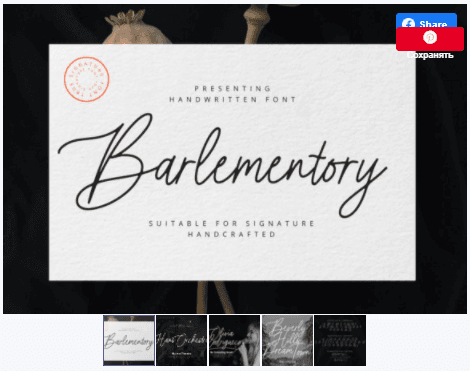
Barlementory Font
Barlementory — плавный рукописный шрифт с элегантным оттенком, идеально подходящий для ваших любимых проектов. Влюбитесь в его невероятно уникальный и неподвластный времени стиль и используйте его для создания впечатляющих дизайнов!